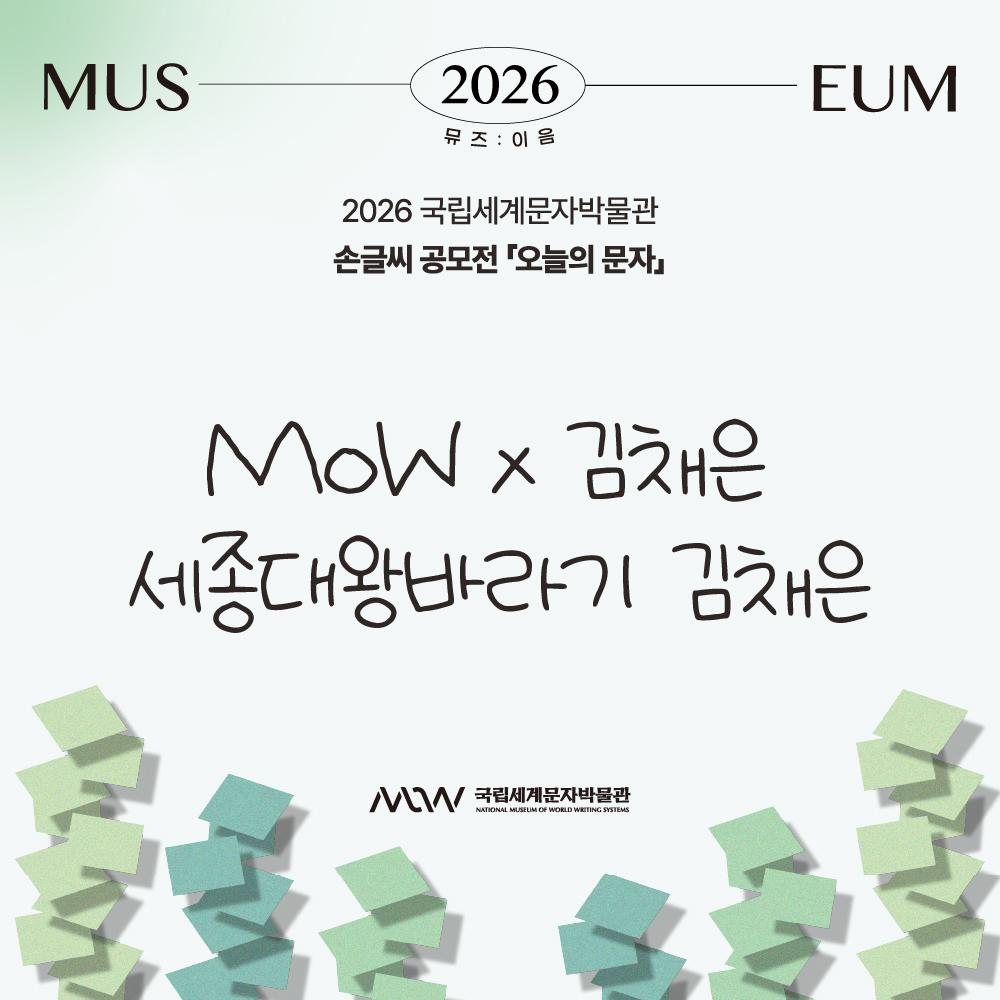
그리운 세종대왕바라기 김채은
Griun Sejong Baragi KimChaeeun
그리운 세종대왕바라기 김채은 소개
2026 국립세계문자박물관 손글씨 공모전 <오늘의 문자> 이 폰트는 2026 국립세계문자박물관 손글씨 공모전 <오늘의 문자> 수상자의 손글씨를 바탕으로 제작되었습니다. 수상자의 정갈하고 따뜻한 손글씨의 특징을 디지털 폰트에 담아, 손글씨만의 자연스러운 개성과 손으로 글씨를 쓰는 감성을 디지털 환경에서도 이어갈 수 있도록 구현했습니다.